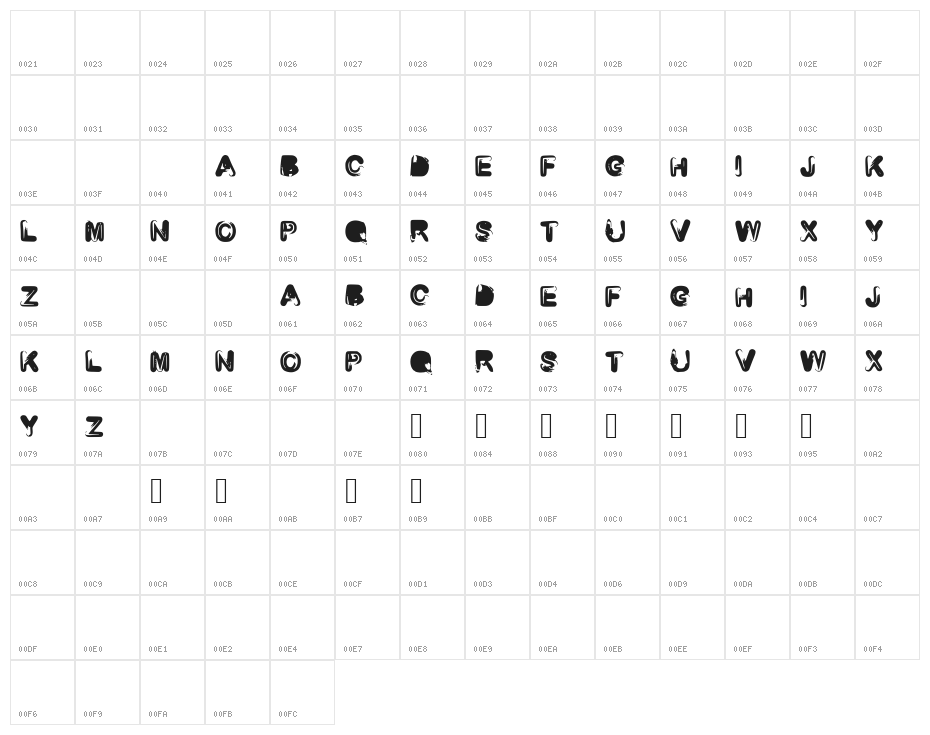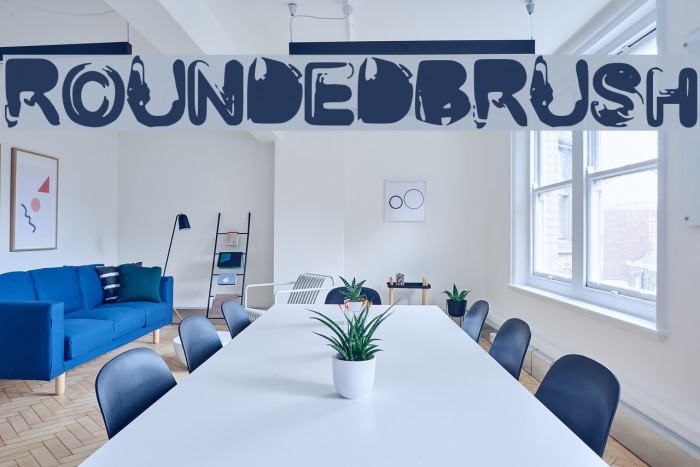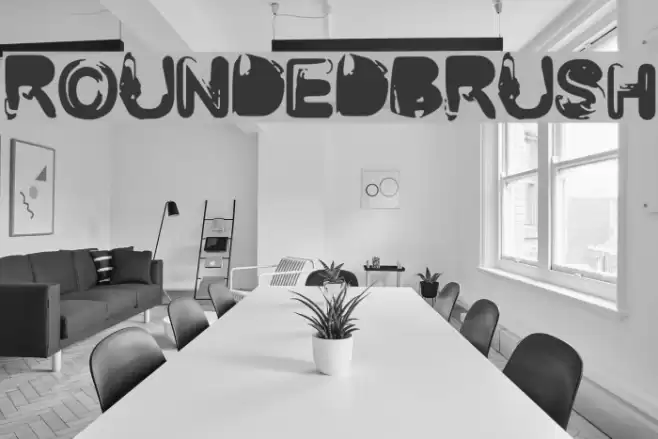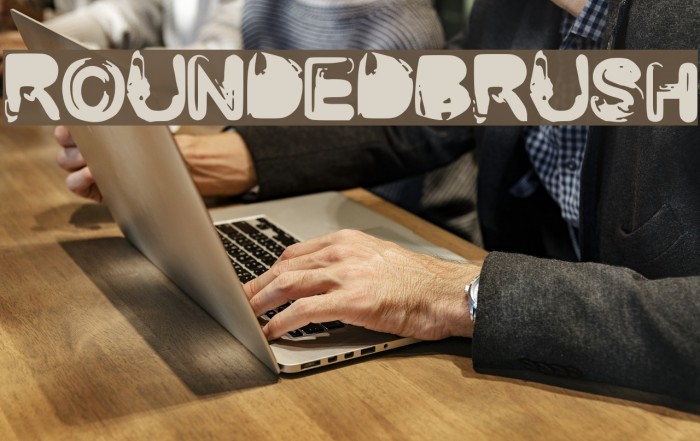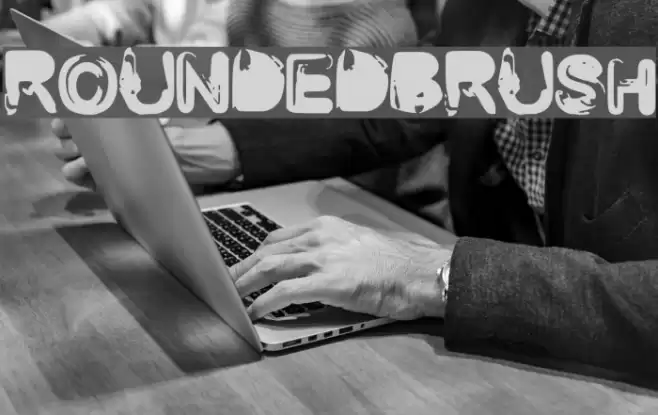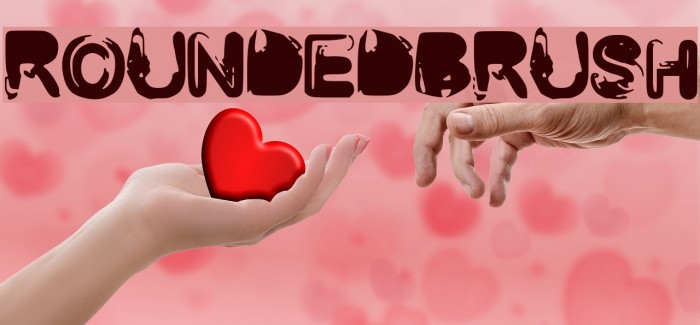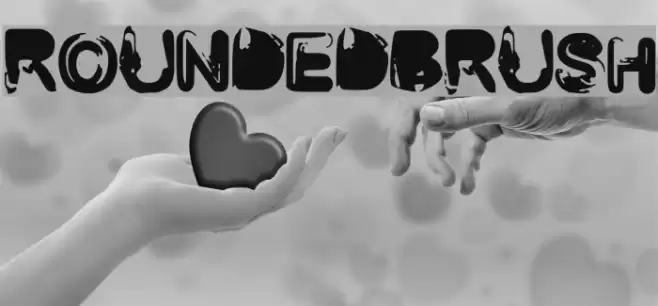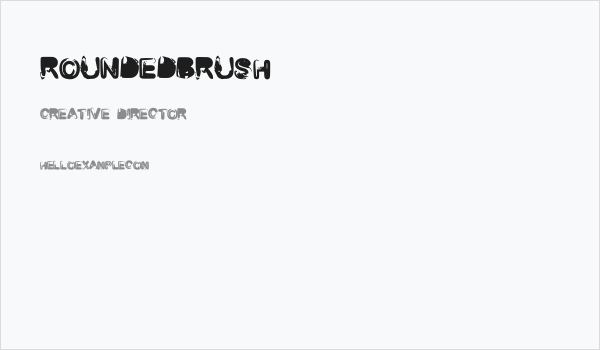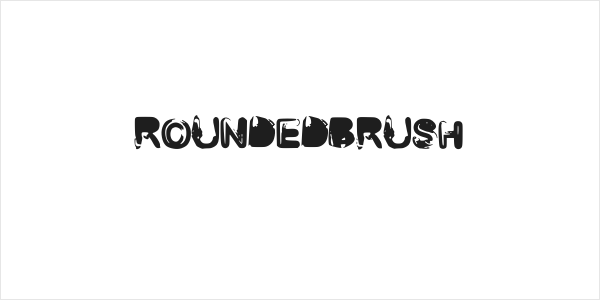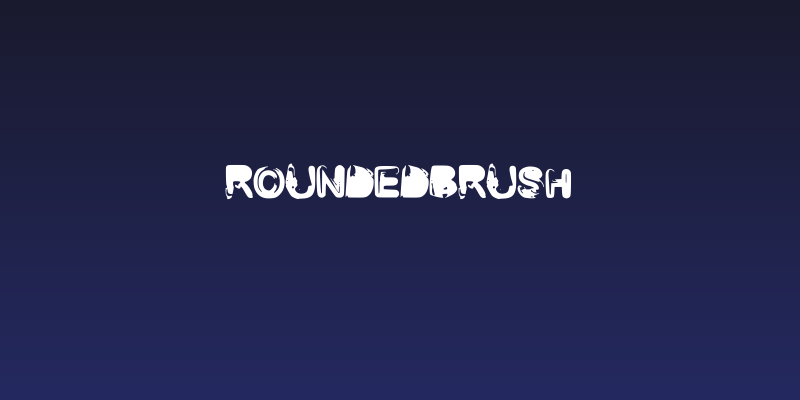
RoundedBrush Font
| Categorias | Fancy |
| Estilo geral | Modern, Artistic |
| Projetos propostos | Perfect for posters, album covers, branding, and any creative project that needs a bold, artistic touch. |